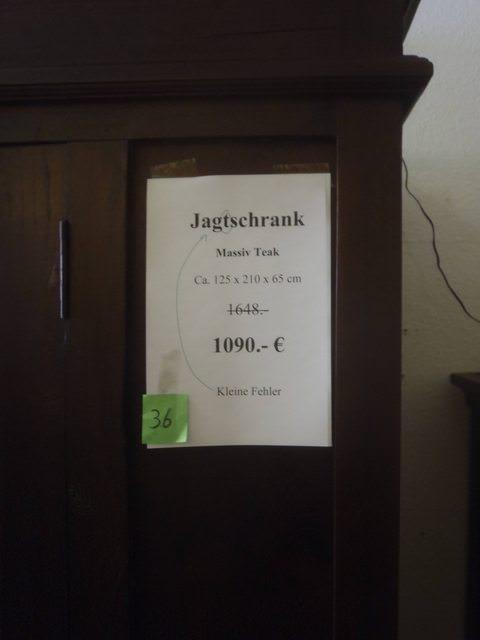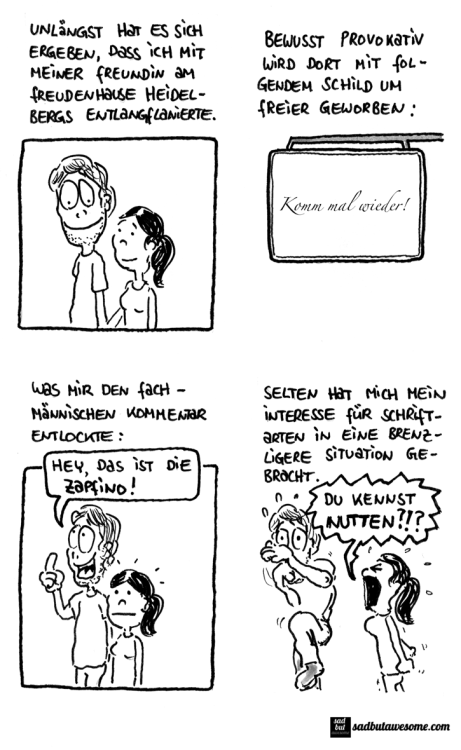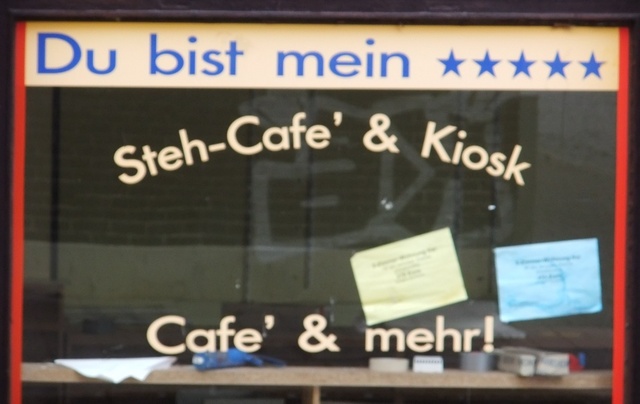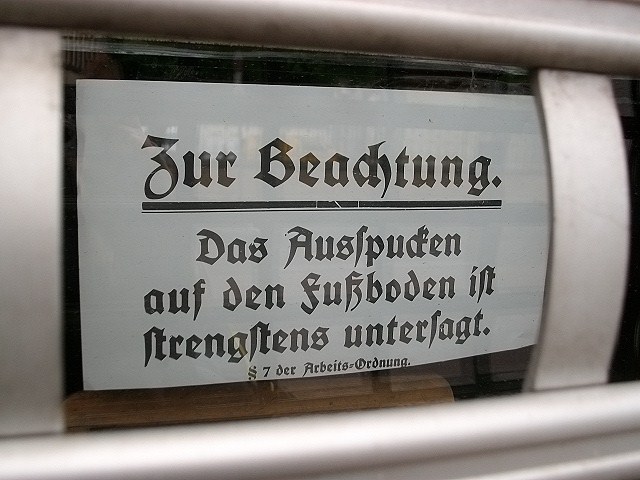
Ich vermute mal, daß durch mannhafte Flüsse wie Rhein und Neckar Abkürzungen wie a/R. oder a/N. so verbreitet waren, daß man dann auch bei der Saale nach dem Schema a/Fluß verfuhr.
Wer weiß? Aber sind die meisten deutschen Flüsse nicht weiblich? Die Donau, die Elbe, die Havel, die Spree, die Weser, die Ruhr? Außer Rhein und Neckar fallen mir im Moment sogar gar keine männlichen deutschen Flüsse ein, während ich die andere Liste nahezu endlos fortsetzen könnte.
Vielleicht liegt es ja daran, dass die Präposition einfach für wichtiger gehalten wurde als der Artikel – und letzterer dann eben in der Abkürzung wegfallen durfte. :-?
Wer weiß? Aber sind die meisten deutschen Flüsse nicht weiblich? Die Donau, die Elbe, die Havel, die Spree, die Weser, die Ruhr? Außer Rhein und Neckar fallen mir im Moment sogar gar keine männlichen deutschen Flüsse ein, während ich die andere Liste nahezu endlos fortsetzen könnte.
dazu etwas im spiegligen zwiebelfisch.
Eindeutig die ſʒ-Form. ;-)
Ralf: Dein Schild? :-?
Eindeutig die ſʒ-Form.
Macht doch nichts! ;-) Ich denke mal, dass es den meisten Leuten einfacher fallen sollte, das ẞ handschriftlich so zu schreiben – zumindest wenn es nicht mit dem ß verwechselt werden soll. Auf alle Fälle fügt es sich hier prima ins Schriftbild ein.
Variation des Themas Deppen-Apostroph:
Das Cafe' ist übrigens geschlossen. Vermutlich hatte der Cafe' dieselbe Qualität wie die Typographie?
Wo hast Du die denn alle aufgetrieben? Dieser riesige Monotype-Saal, und niemand mit Ohrschützer … :neenee:
Für die, die es nicht mehr erlebt haben: Die Monotype wird mit Preßluft betrieben und macht bei jedem Tastenanschlag ordentlich Lärm, da dann ein Loch in den Lochstreifen gestanzt wird. Die
als die Tastmaschine,
Impressionen aus dem Möbelladen …
Ist da ein "o" zuviel?
Hängt im Flughafen Düsseldorf.
Wer – wie ich – das "gebraucht" in Ralfs Ausspruch auch ohne "b" lesen kann, hat hier halt das schnellere Auge auf der Lunge. :schonklar:
§ 7 der Arbeits-Ordnung
Gilt das jetzt für die Angestellten oder für die Kunden :-?